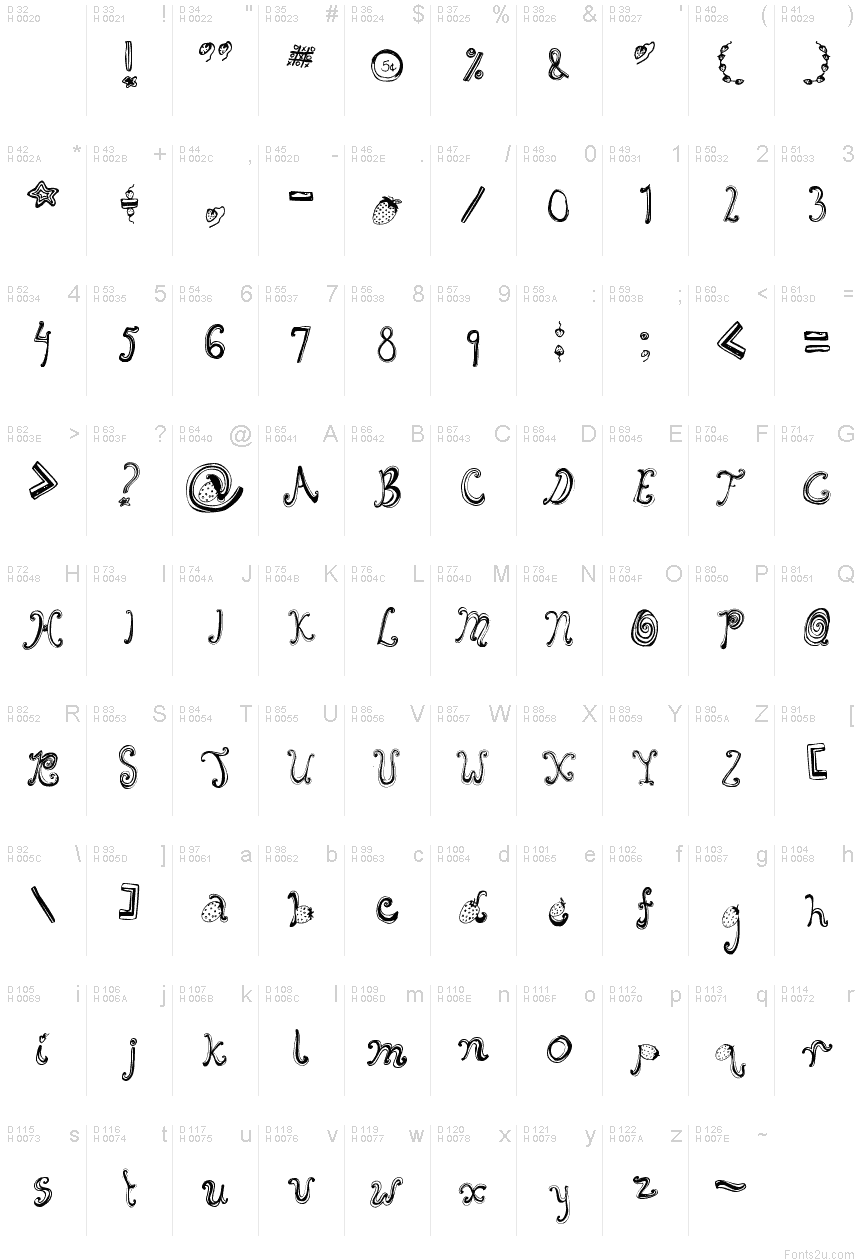
Starberry Swirl Delight di Little Starseed è un carattere display decorativo, gratuito e stravagante, dal sapore artigianale tipico dei libri di fiabe. Le lettere mescolano volute e motivi a forma di fragola, rendendo il font un ibrido tra lettering e illustrazione, con curve morbide e contorni irregolari che lo rendono giocoso anziché costruito.
È perfetto per packaging a tema fragola, copertine di libri per bambini, menù su lavagna, titoli per scrapbook e inviti a feste, dove il carattere può fare da elemento decorativo principale. Essendo un font gratuito, è ideale anche per titoli brevi, bozze di loghi e targhette che richiedono un tocco dolce e fatto in casa, senza apparire banale.